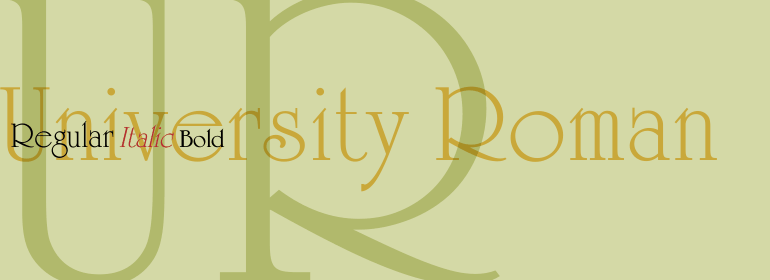
University™ Roman
University™ Roman,这款字体结构工整、笔画清晰,兼顾美观与易读性,适用于标题、正文、海报、包装、LOGO 等多种场景。字形优雅稳定,风格百搭耐看,适配日常排版与创意设计,让文字呈现更舒适、更具质感。University™ Roman一笔一画,皆是细节,以均衡的比例、流畅的线条打造舒适视觉体验,字形端正大气,风格简约现代。无论是商业设计、品牌宣传还是日常排版,都能轻松驾驭,让文字更有格调与力量。University™ Roman字体下载。
自1972年由Letraset引入以来被广泛使用的一种倍受欢迎的字体。此改进的新版本包括许多自由流畅的花饰替代字符,使设计人员具有更多的实验自由。由Phillip Kelly在Letraset Type Studio中根据他和Mike Daines的原始设计制作。
A popular typeface that has been widely used since its introduction by Letraset in 1972. This new and improved version includes many free-flowing swash alternatives that give designers more freedom for experimentation. Produced by Phillip Kelly in the Letraset Type Studio based on his and Mike Daines' original design.